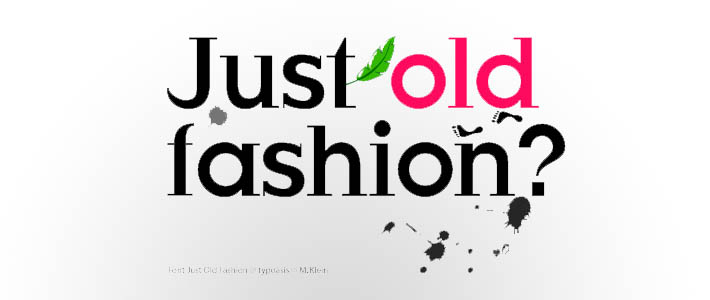
Come ogni settimana siamo arrivati all’appuntamento con il nostro font inspiration, oggi vi consiglio Aka Dora, davvero molto elegante e dal look retrò antico, adatto a molte occasioni.
Ecco una preview completa del font: